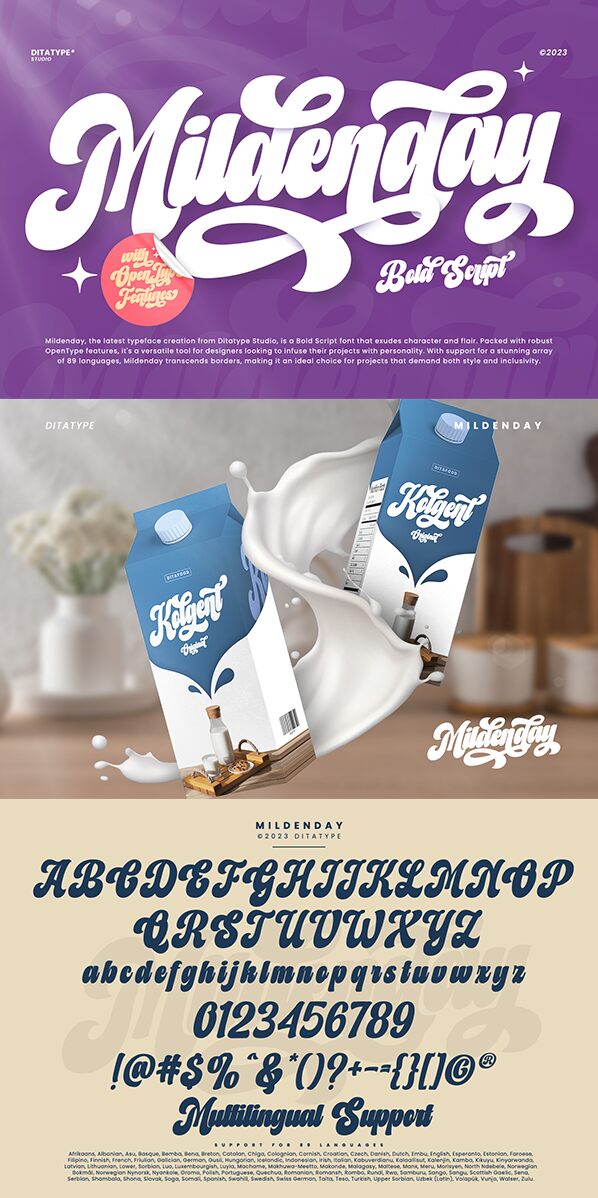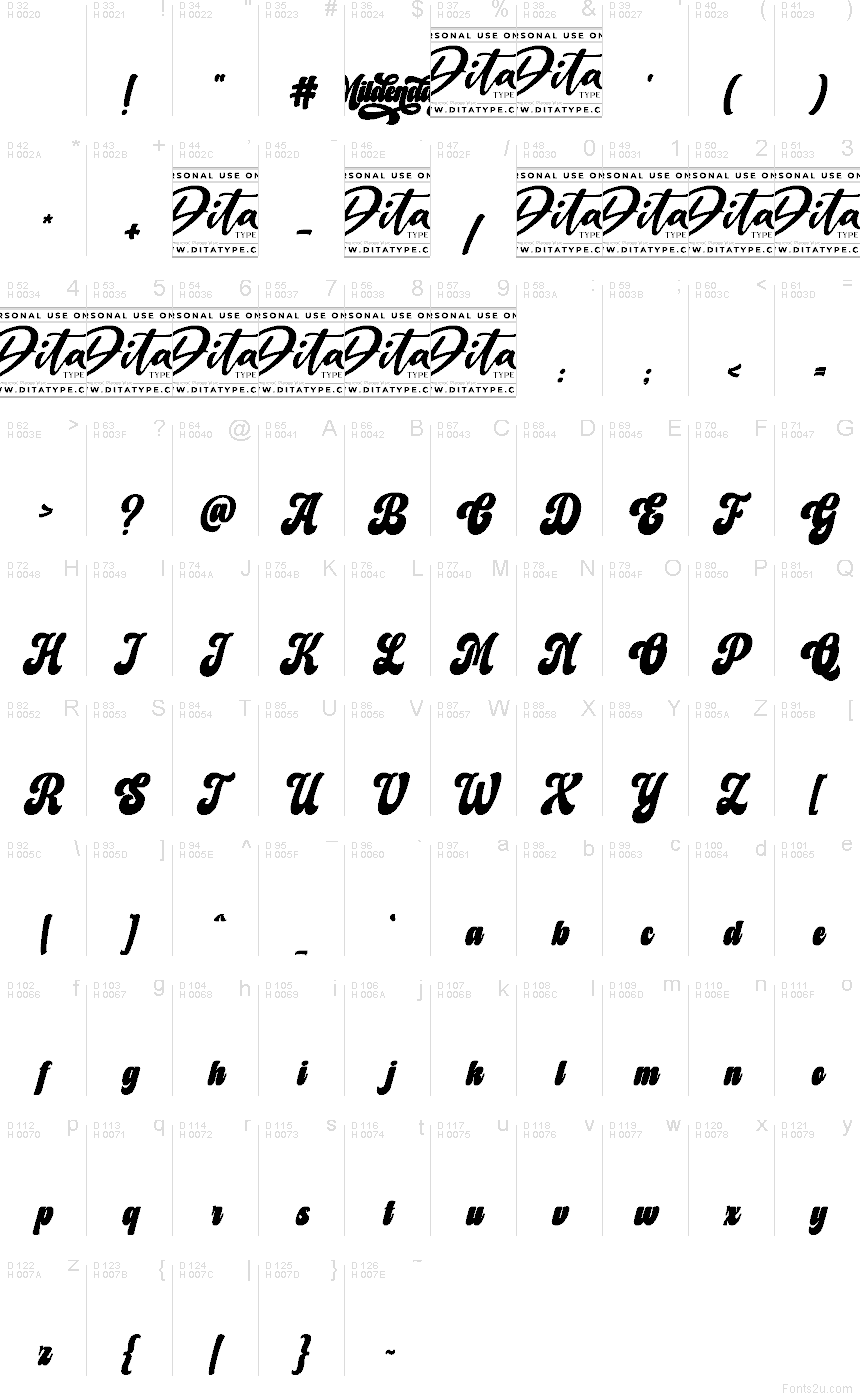
Písmo Mildenday od Ditatype je bezplatný brush font s plynulou linkou a zaoblenými, ručně malovanými spoji. Písmena mají živý sklon a široké křivky s několika dlouhými smyčkami, které dodávají nápisu osobní, rukopisný rytmus.
Mildenday se skvěle hodí pro loga, svatební oznámení, citáty na sociální sítě, obalový design a branding ve stylu podpisu, protože vnáší do návrhu kreslený a neformální nádech, aniž by působil hrubě. Hodí se také pro krátké nápisy na plakátech, jídelní lístky v kavárnách či přání, pokud chcete, aby text působil výrazně a lidsky.